スマートな字の書き方
筆ペンや児童の硬筆のお手本の揮毫やボールペンや筆ペンの本の執筆と共に、四谷学院と産業能率大学の通信教育のテキストを執筆する日本書蒼院副理事長(松戸会会長)による岡田崇花氏が監修と手本を手掛けた「スマートな字の書き方」が玄光社から2018年5月31日に発売される。
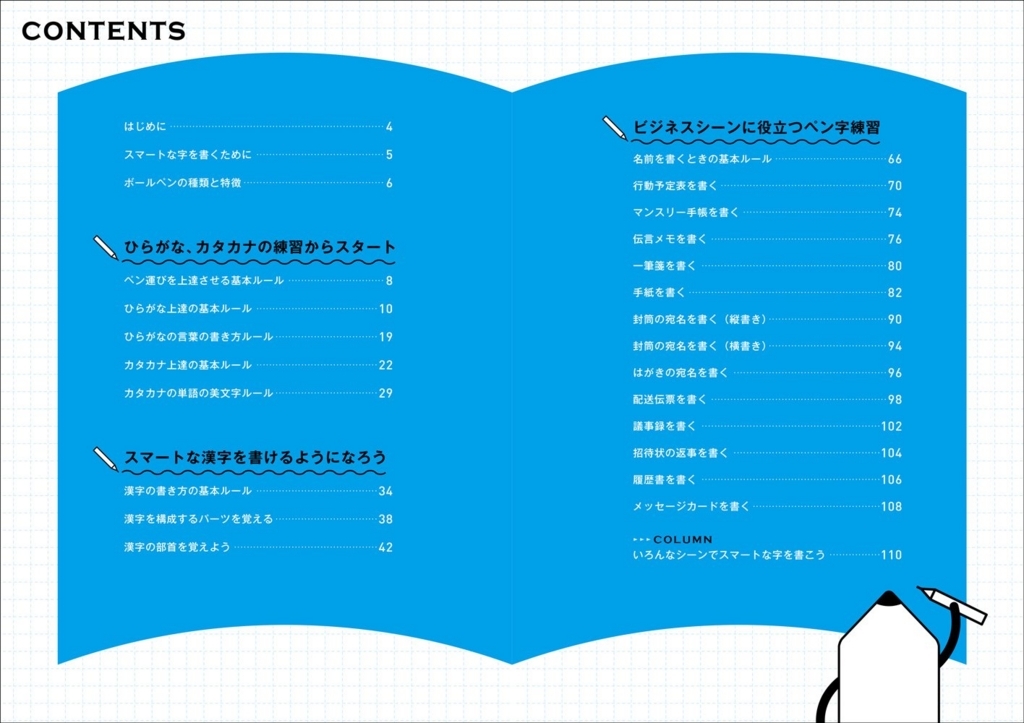
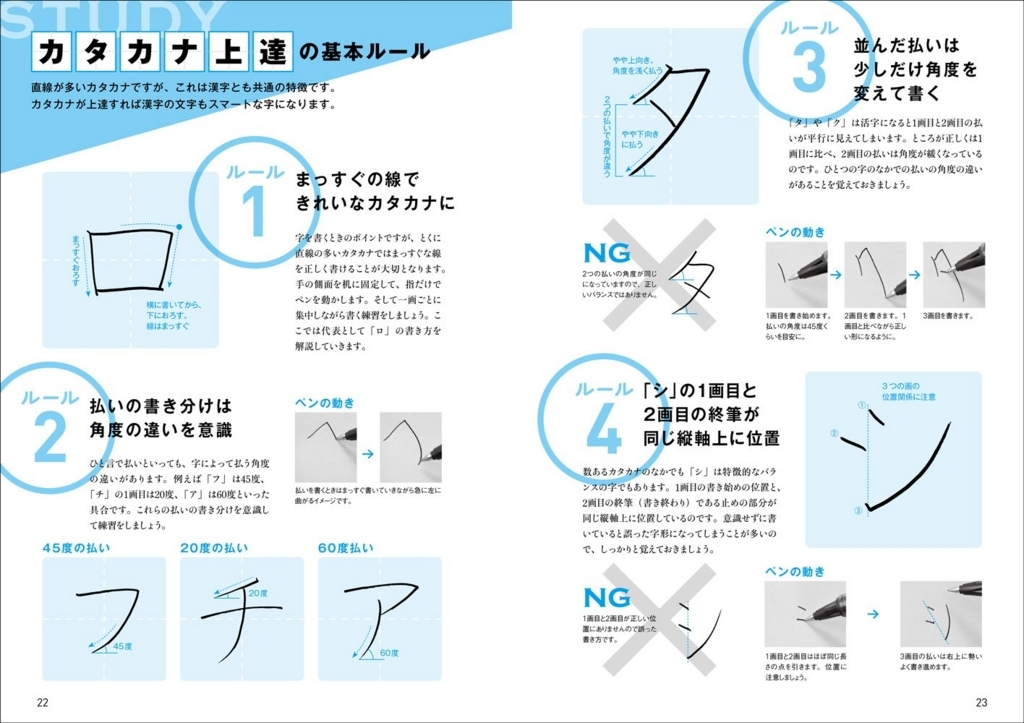
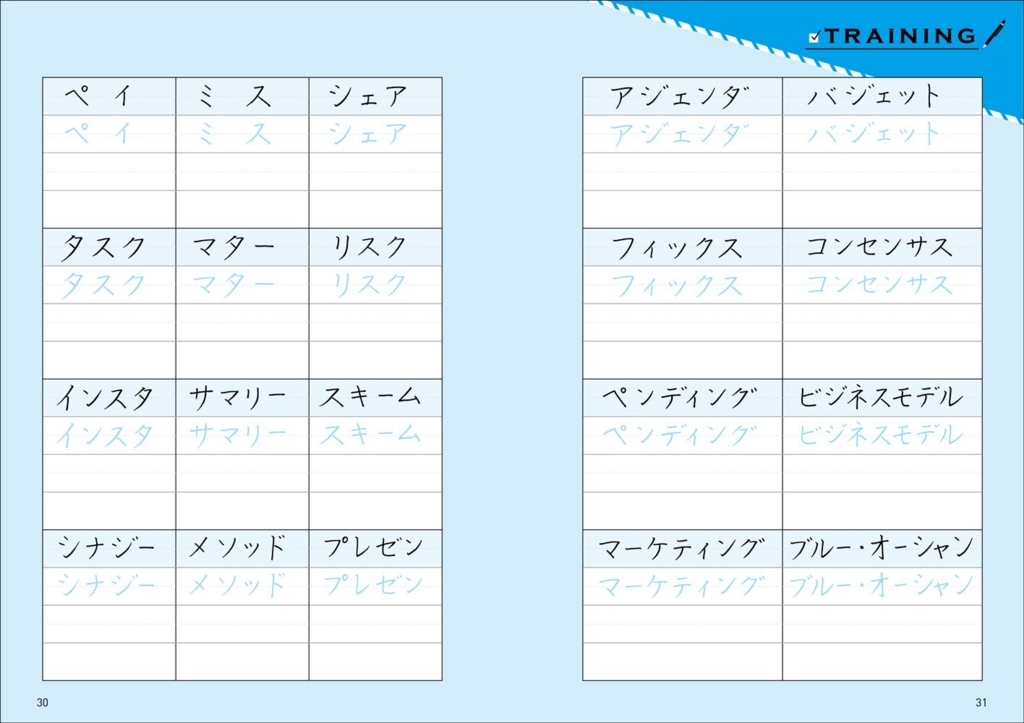
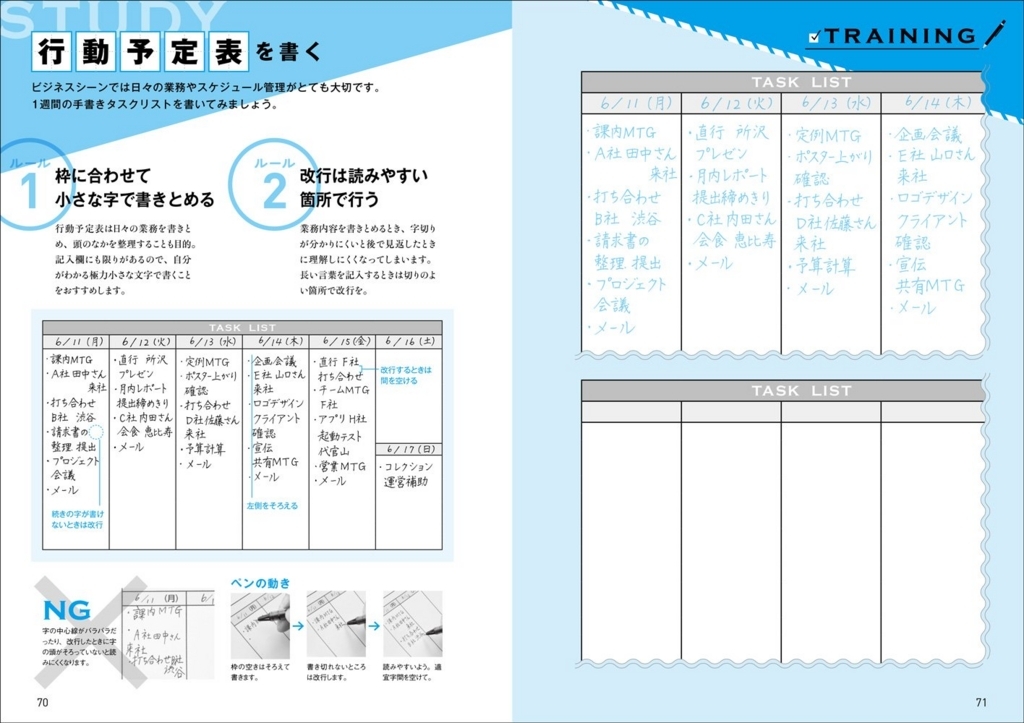
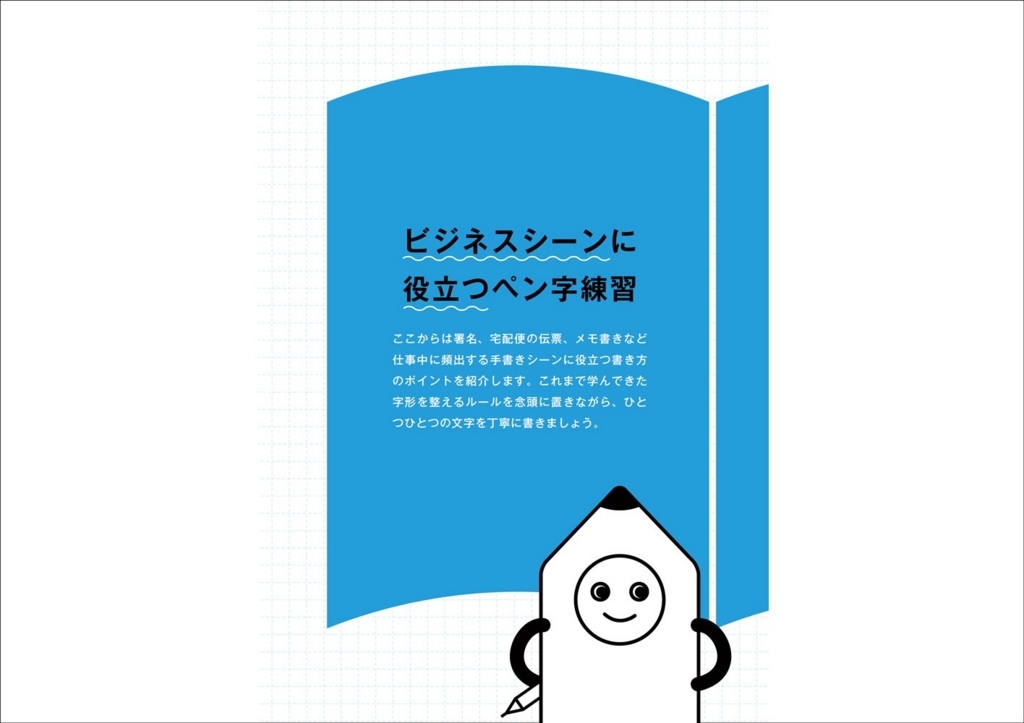
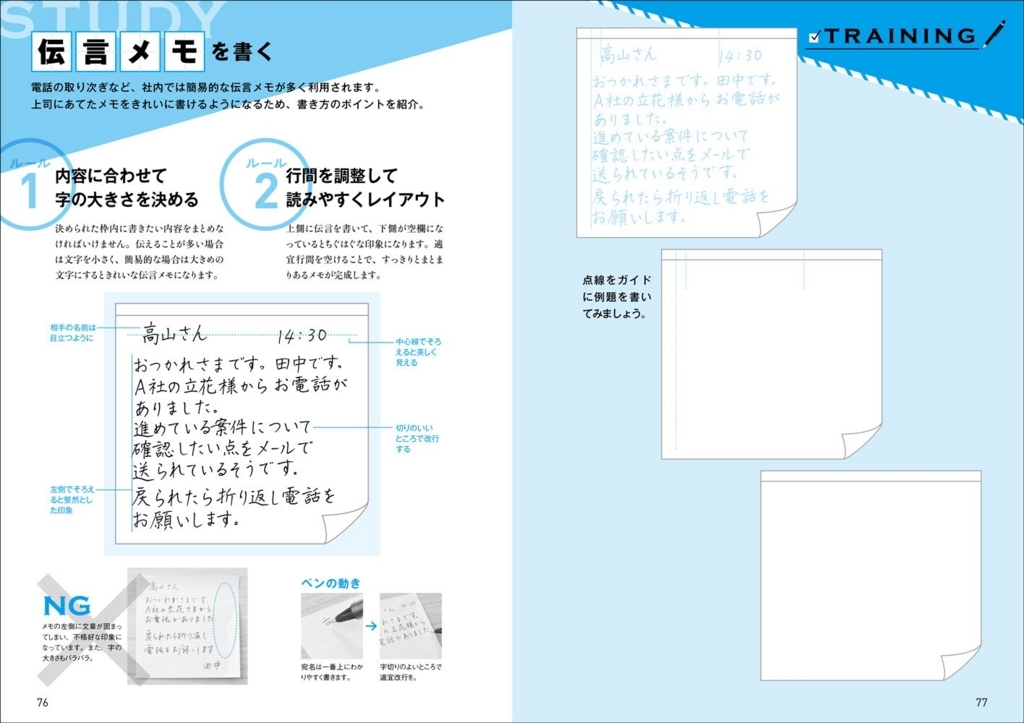
パソコンが普及している現代では、仕事の多くがデータ作成やメールで行われ、スマートフォン片手に会議など、文字を書く機会が減っています。
それ故に文字を書くこと事態に対して必要意識を持つ人が減ってきているようです。
「どうせ手書きでかくこと事態あまりないのだから……」と高をくくっている人は要注意かも!
もしかして貴方の仕事いつまでも評価されないのは、汚い文字のせいかもしれません。
ちょっとした伝言メモ、宅配便の伝票で貴方の仕事の印象が変わってくるかも。
ちょっとしたメモ書き、ノートの書き込み、ホワイトボードの文字など、
実は多くの人があなたの文字を見ています。
美しい文字にたいして希薄な時代だからこそ、きれいな文字を書くことができれば、社内、社外での評判も上がることでしょう。
スマートな仕事ができるビジネスパーソンの一助となる美しい文字を是非かけるようになりましょう。1日1分、1日1文字からでも構いません。
美しい文字のルールに慣れ親しむ小さな積み重ねがあなたの文字を劇的に美しく変化させます。楽しみながら挑戦してください。
【目次】
スマートな字を書くために
ボールペンの種類と特徴
ひらがな、カタカナの練習からスタート
ペン運びを上達させる基本ルール
ひらがな上達の基本ルール
ひらがなの言葉の書き方ルール
カタカナ上達の基本ルール
カタカナの単語の美文字ルール
スマートな漢字を書けるようになろう
漢字の書き方の基本ルール
漢字を構成するパーツを覚える
漢字の部首を覚えよう
ビジネスシーンに役立つペン字練習
名前を書くときの基本ルール
行動予定表を書く
マンスリー手帳を書く
伝言メモを書く
一筆箋を書く
手紙を書く
封筒の宛名を書く(縦書き)
封筒の宛名を書く(横書き)
はがきの宛名を書く
配送伝票を書く
議事録を書く
招待状の返事を書く
履歴書を書く
メッセージカードを書く
いろんなシーンでスマートな字を書こう
岡田崇花Profile●日本書蒼院副理事長(松戸会会長)
日本書蒼院の教材である書蒼でペン、筆ペンや児童の硬筆、半紙、条幅とお手本を揮毫。ボールペンや筆ペンの本の執筆と共に、四谷学院と産業能率大学の通信教育のテキストを執筆。また、教え子が産業能率大学主催によるボールペン字大賞(文部科学大
臣賞受賞)、環境書道展(県知事賞受賞)などで受賞するなど、指導者としてもさまざまな実績を持つ。書蒼誌のペン・筆ペンの師範、カルチャー講師、書道講師など関東での活動に力を入れている。著書に『4週間で筆文字がきれいになる! 書き込み式 筆ペン
練習帳』(日本文芸社)、『枕草子を書く 現代文と共に』(日本習字普及協会)などがある。